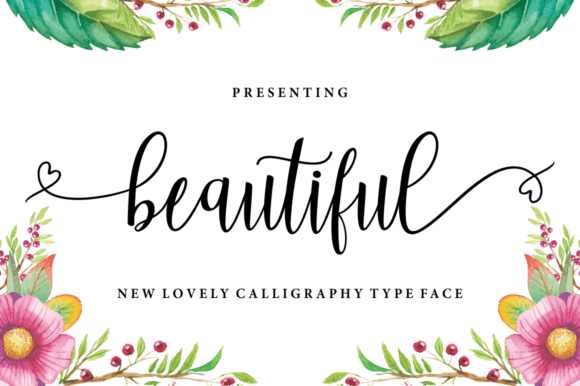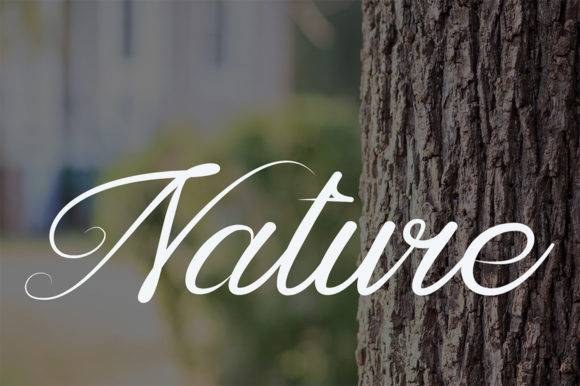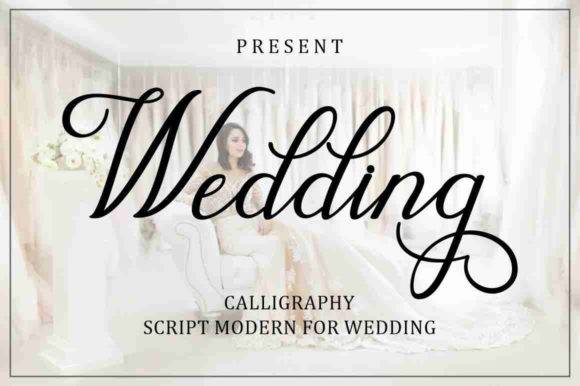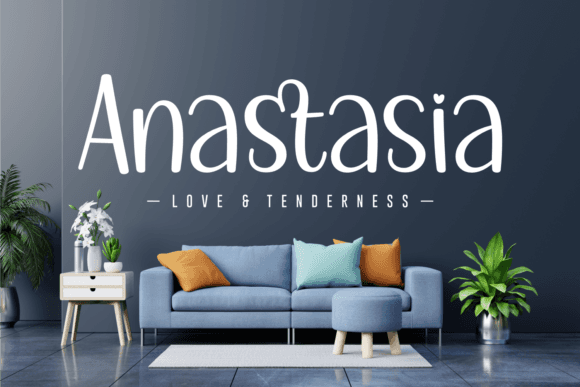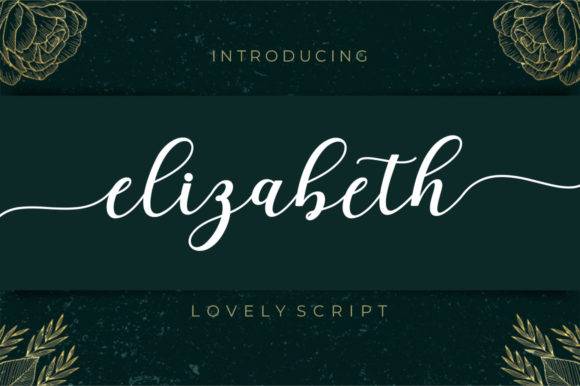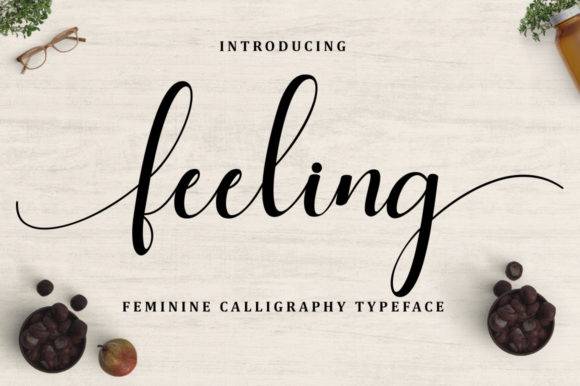
Explorando diferentes estilos de fonte
Nossa coleção apresenta uma gama diversificada de estilos de fontes, cada um com seu caráter e propósito únicos. De scripts elegantes a fontes manuscritas divertidas, há algo para cada projeto.
Fontes de script para elegância e criatividade
Fontes manuscritas para um toque pessoal
Fontes elegantes para designs sofisticados
Aspectos técnicos das fontes gratuitas
Entender os aspectos técnicos das fontes pode ajudar você a aproveitar ao máximo seus projetos de design. Aqui estão alguns pontos-chave a serem considerados:
Compatibilidade de fontes e glifos
Codificação PUA
Muitas de nossas fontes, como Wedding Font e Elizabeth Font, são codificadas em PUA (Private Use Area). Isso significa que você pode acessar facilmente todos os glifos e swashes, aumentando suas possibilidades de design.
Considerações de compatibilidade
Embora a maioria das nossas fontes seja versátil, algumas podem ter problemas específicos de compatibilidade. Por exemplo, a fonte Anastasia não é compatível com o Canva. Sempre verifique os detalhes da fonte antes de incorporá-la aos seus projetos.
Acessando Glifos e Florais
Fontes como Luxury Font e Feeling Font oferecem designs de letras e swashes exclusivos. Esses caracteres adicionais podem dar um toque especial aos seus designs, especialmente para logotipos, branding e texto decorativo.
Escolhendo a fonte certa para seu projeto
Selecionar a fonte perfeita é crucial para um design eficaz. Considere estes fatores ao escolher uma fonte da nossa coleção de fontes gratuitas :
Pontos-chave
- Legibilidade: Quão facilmente a fonte pode ser lida, especialmente em tamanhos pequenos?
- Tipografia: A fonte está alinhada ao tom, estilo e público do projeto?
- Compatibilidade: A fonte funcionará com o software de design e as plataformas utilizadas?
- Exclusividade: A fonte oferece uma aparência ou toque único que a diferencia das demais?
- Escalabilidade: Quão bem a fonte é dimensionada, tanto para cima quanto para baixo, sem perder qualidade?
- Emparelhamento de fontes: quão bem a fonte combina com outras fontes e elementos de design?
Conclusão